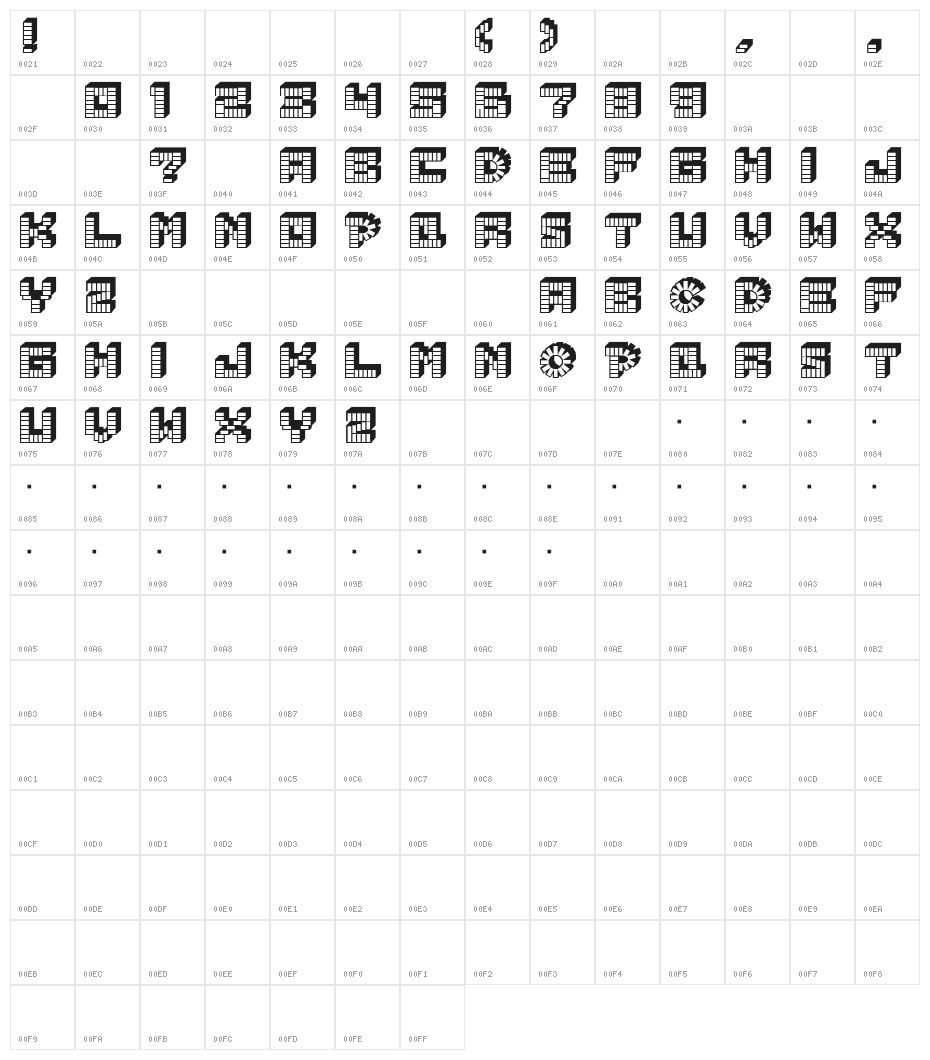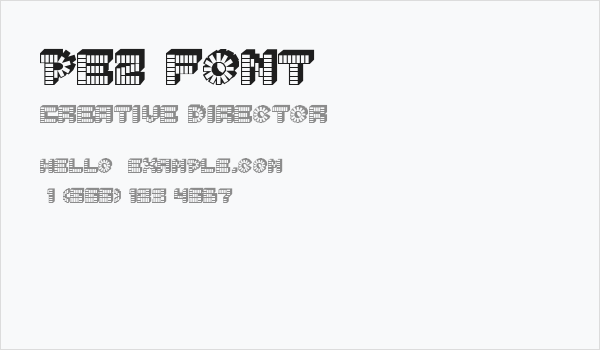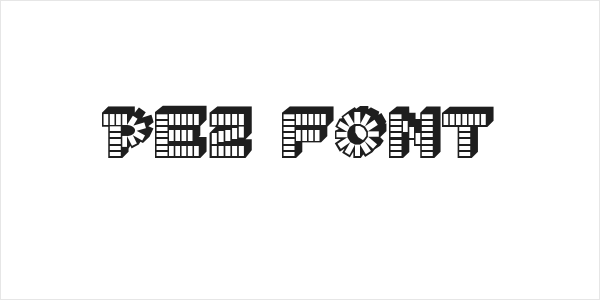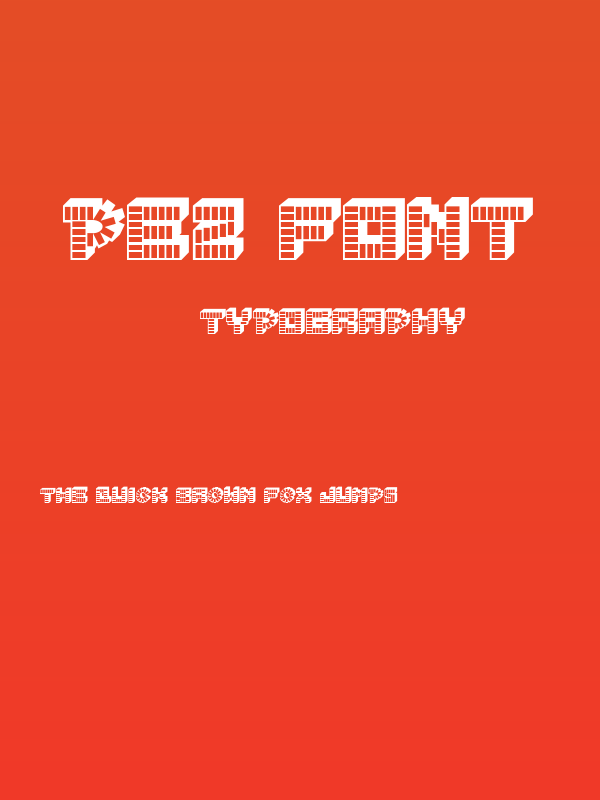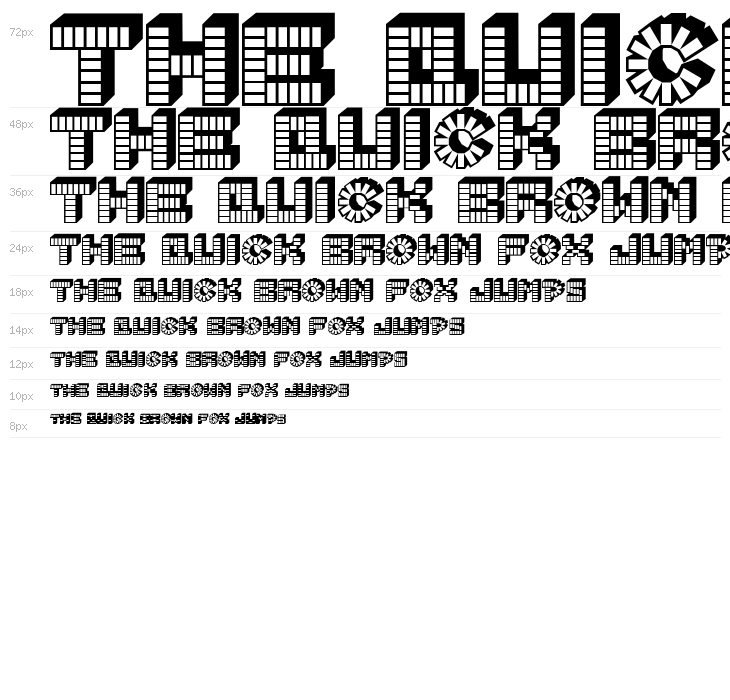
PEZ font Font
| Stile generale | Playful, Modern |
| Progetti proposti | Ideal for use in children's books, toy packaging, playful branding, or any project that requires a fun and eye-catching typeface. |